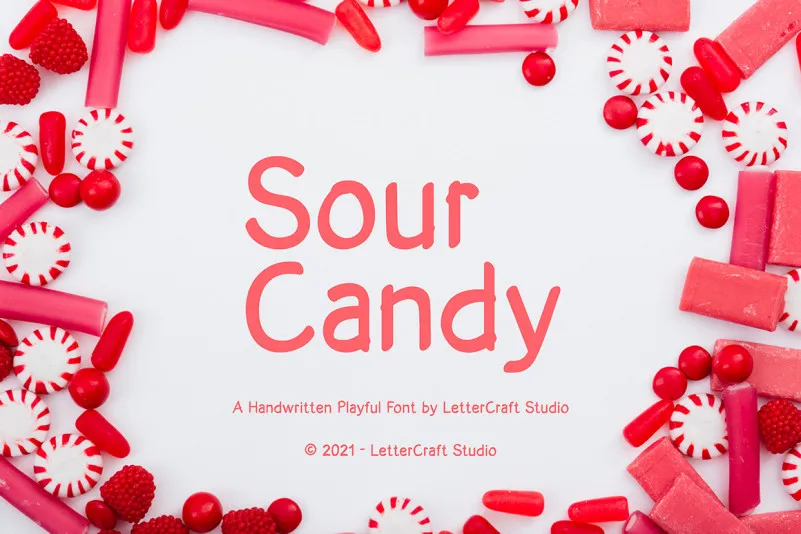
Sour Candy Font – Fonte Grátis
Sour Candy Font
A Fonte ‘Sour Candy’ é uma proposta divertida e encantadora para qualquer criatividade que você possa ter. Ideal para tornar seus projetos únicos, esta fonte leva seu design do papel para um nível incrivelmente visual, fazendo com que suas ideias chamem a atenção dos mais qualificados e apaixonados por arte. Aproveite o tom descontraído e vibrante da ‘Sour Candy’ como uma forma única de expressar sua personalidade ou transmitir um conceito específico em qualquer projeto gráfico. Não importa se você está criando cartazes, design editorial ou até mesmo elementos digitais divertidos; esta fonte vai garantir que seu trabalho seja o ponto de destaque no meio da multidão. Envolva seus seguidores com uma coração cheio de alegria e entusiasmo, é assim que a ‘Sour Candy’ pode ajudá-lo a fazer isso.